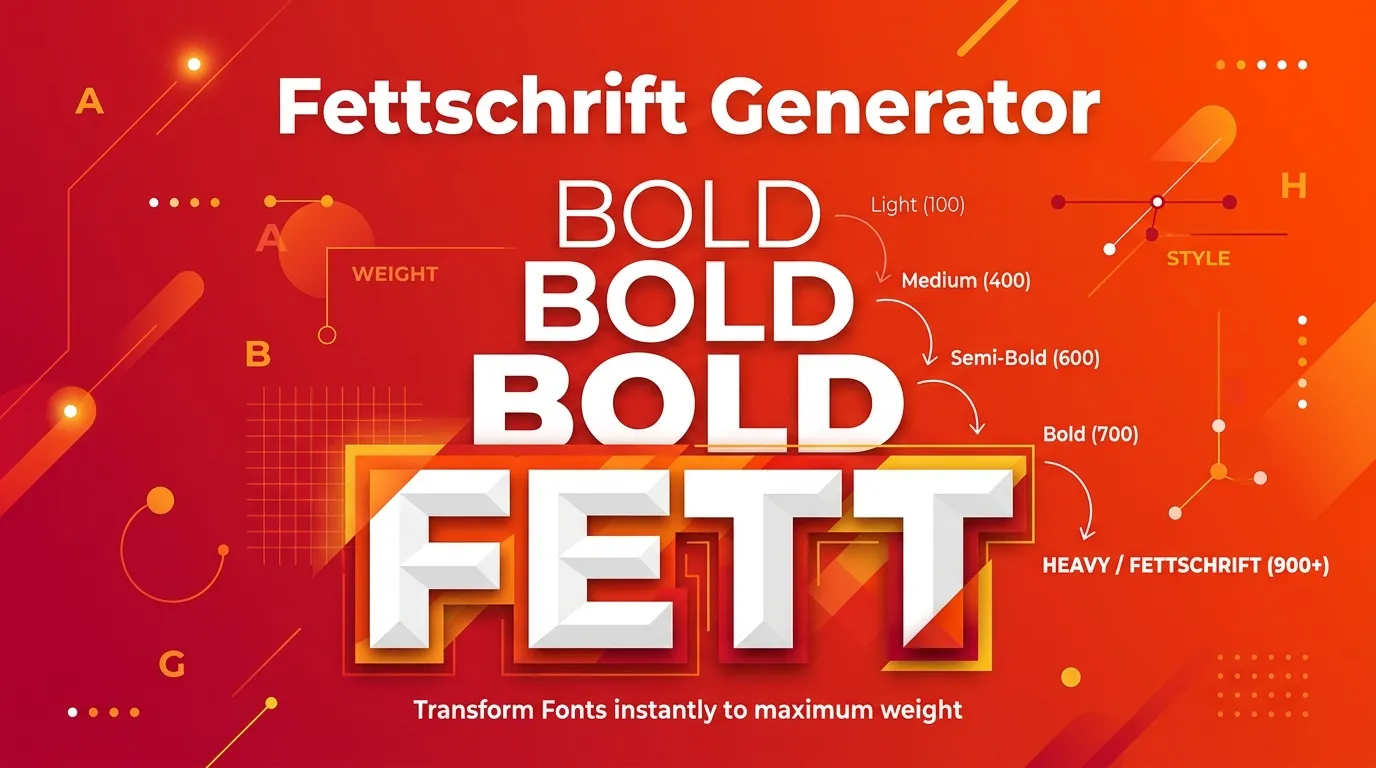
Fettschrift Generator
Wandle deinen Text in Sekunden in fette Unicode-Schrift um: kopieren & einfügen für Instagram, WhatsApp, LinkedIn & mehr. Kostenlos, ohne Anmeldung, direkt im Browser.
Hinweis: Umlaute (ä, ö, ü, ß)
Deutsche Umlaute und ß haben keine Fettschrift-Entsprechung im Unicode-Standard und erscheinen daher in normaler Schrift neben den umgewandelten Buchstaben. Das ist eine unvermeidliche technische Einschränkung aller Fettschrift-Generatoren, nicht ein Fehler unseres Tools.
Barrierefreiheit: Unicode-Sonderzeichen werden von Screenreadern (VoiceOver, TalkBack) oft nicht korrekt vorgelesen. Für zugängliche Websites empfehlen wir semantisches HTML-Formatting statt Unicode-Zeichen.
Wähle aus verschiedenen Fettschrift-Stilen: Serif-Fett, Sans-Fett, Fett-Kursiv, Fett-Fraktur und mehr. Klicke auf die Kategorie "Fett" zum Filtern.
Fettschrift für Instagram-Bio und LinkedIn-Posts
Fette Schrift hebt wichtige Informationen in deiner Instagram-Bio sofort hervor: ideal für deinen Namen, Beruf oder Call-to-Action. Auf LinkedIn sind fette Unicode-Zeichen besonders beliebt, um Posts strukturierter und lesbarer zu machen: Aufzählungen, Zwischenüberschriften und Schlüsselwörter in Fettschrift erhöhen die Verweildauer und die Interaktionsrate nachweislich.
Wichtig zu wissen: Auf Social-Media-Plattformen wird Unicode-Fettschrift von der Plattform-Schriftart übernommen und korrekt dargestellt. Das Ergebnis ist plattformübergreifend einheitlich, solange das Gerät des Empfängers Unicode unterstützt.
Besonders effektiv ist Fettschrift in Verbindung damit, kursiven Text zu kombinieren : zum Beispiel für Überschriften in einer Instagram-Bio.
Fettschrift auf WhatsApp: Unicode vs. native Formatierung
WhatsApp bietet zwei Wege zu fettem Text: Erstens die native Formatierung mit *Sternchen*: schreibe *Wort* und es erscheint fett im Chat. Diese Methode funktioniert nur in Nachrichten, nicht im Profilnamen oder Status.
Zweitens Unicode-Fettschrift über unseren Generator: Diese Methode funktioniert überall: in Nachrichten, im Profilnamen, in der Info und im Status. Für maximale Kompatibilität empfehlen wir, in Chats die native *Sternchen*-Formatierung zu verwenden und für Profilbereiche den Generator.
Für noch mehr Wirkung kannst du fette Passagen mit Texte zusätzlich mit einer Unterstreichung zu betonen .
Technische Hintergründe: Was ist Unicode-Fettschrift?
Unicode-Fettschrift ist kein echtes Schriftformat, sondern ein Satz mathematischer Symbole im Unicode-Standard (Blöcke U+1D400-U+1D7FF). Diese Symbole existieren als eigenständige Zeichen: ähnlich wie Emojis: und werden deshalb auf jedem Gerät gleich dargestellt, unabhängig von der installierten Schriftart.
Die praktische Konsequenz: Fette Unicode-Zeichen sind per Copy & Paste überall einsetzbar, wo Text eingegeben werden kann. Der Nachteil ist die eingeschränkte Zeichenunterstützung: Umlaute (ä, ö, ü, ß) sind nicht im mathematischen Unicode-Block enthalten und erscheinen daher in normaler Schrift.
In Kombination mit Fettschrift wirkt durchgestrichener Text für humorvolle Korrekturen besonders wirkungsvoll auf Social Media.
Häufig gestellte Fragen
Alles rund um Fettschrift und Unicode-Sonderzeichen
Was ist ein Fettschrift Generator und wie funktioniert er?
Ein Fettschrift Generator wandelt normalen Text in Unicode-Zeichen um, die wie fette Buchstaben aussehen. Dabei handelt es sich nicht um eine echte Schriftart, sondern um mathematische Unicode-Symbole aus dem Bereich "Mathematical Bold". Diese Zeichen sehen überall gleich aus, weil sie Teil des Unicode-Standards sind: nicht weil eine Schriftart installiert sein muss.
Funktioniert Fettschrift-Text auf Instagram, WhatsApp und Facebook?
Ja, auf allen drei Plattformen funktionieren fette Unicode-Zeichen in Bio-Texten, Bildunterschriften, Kommentaren und Nachrichten. WhatsApp bietet zudem eine native Fettschrift mit *Sternchen* in Chats, die jedoch nur im Chat selbst sichtbar ist: nicht im Profilnamen oder Status.